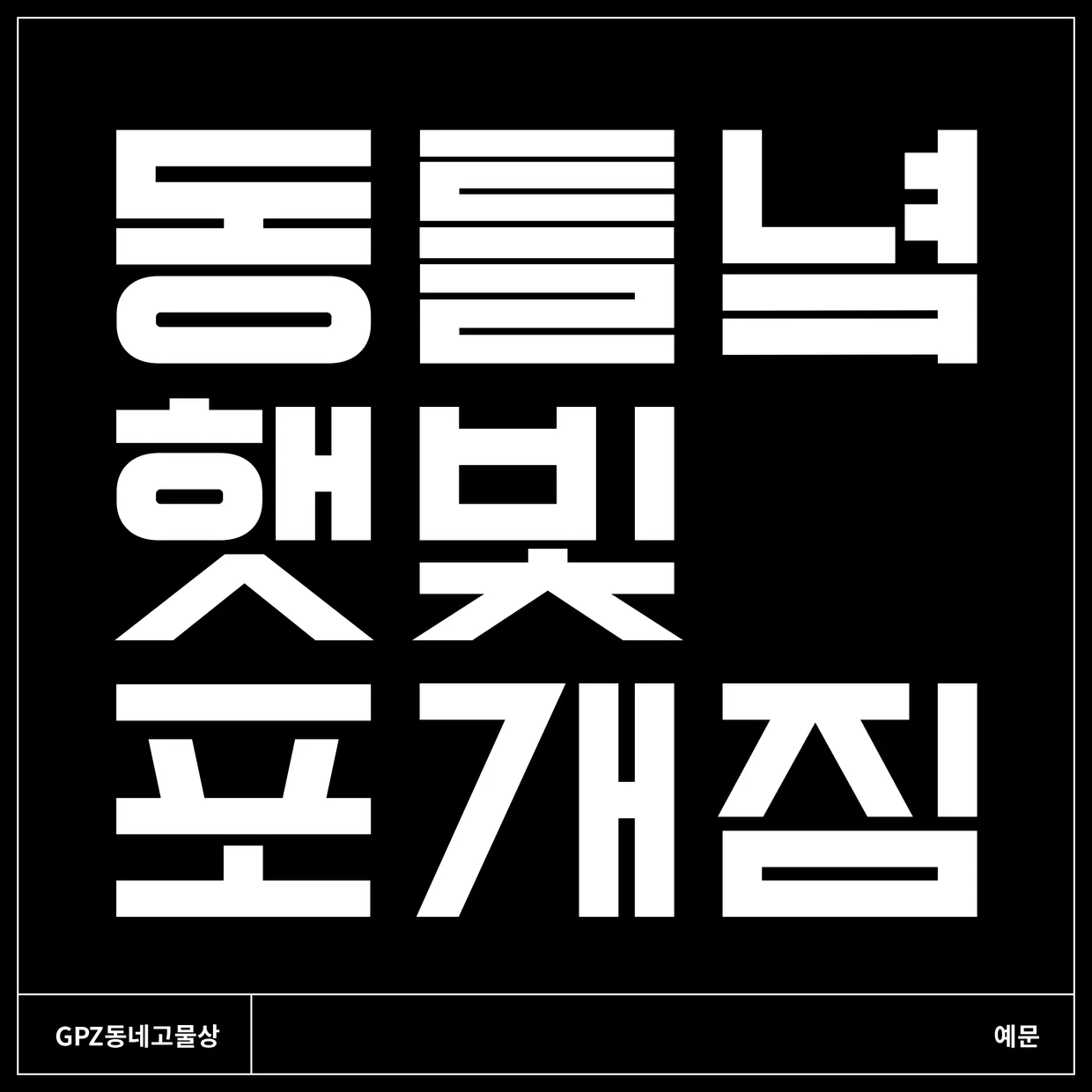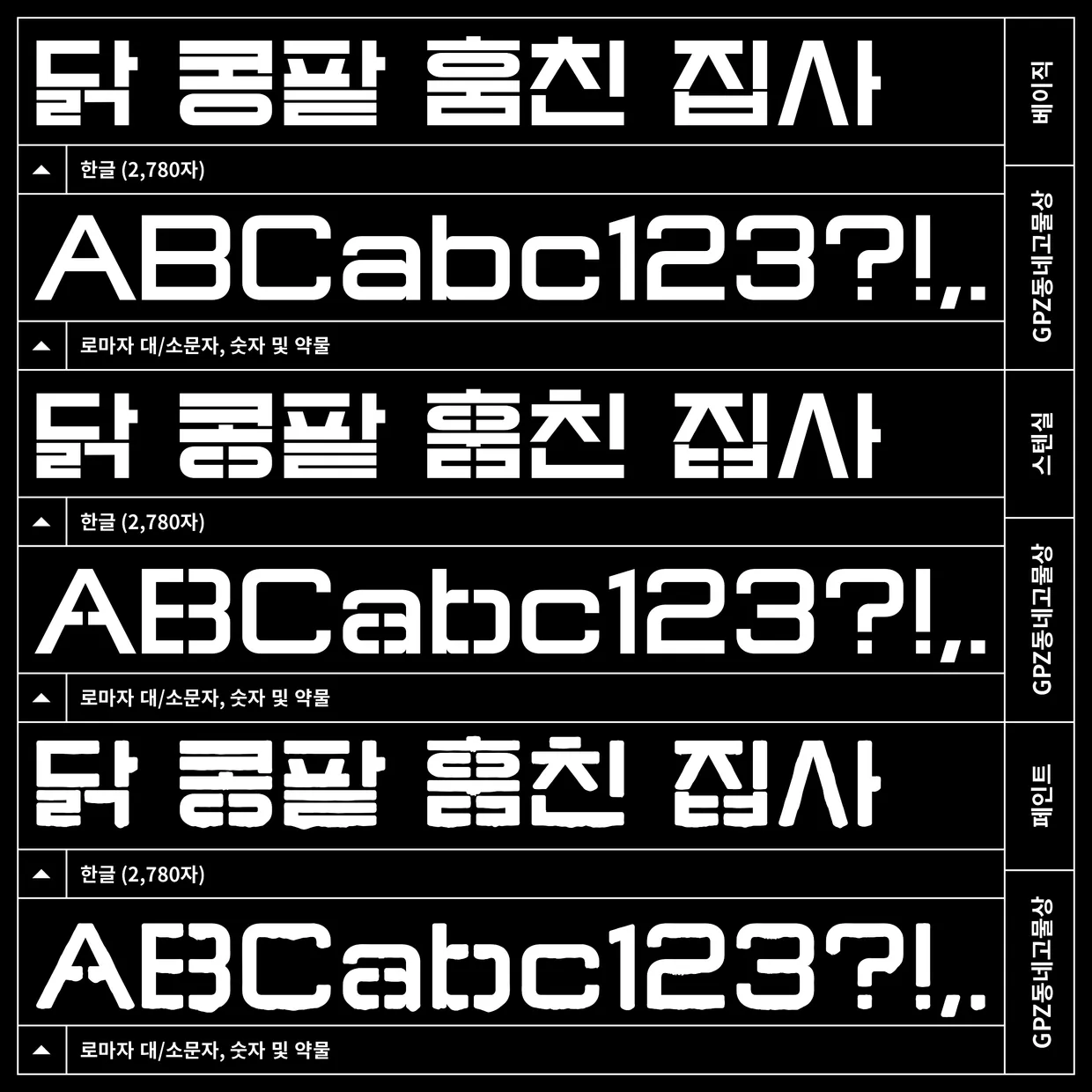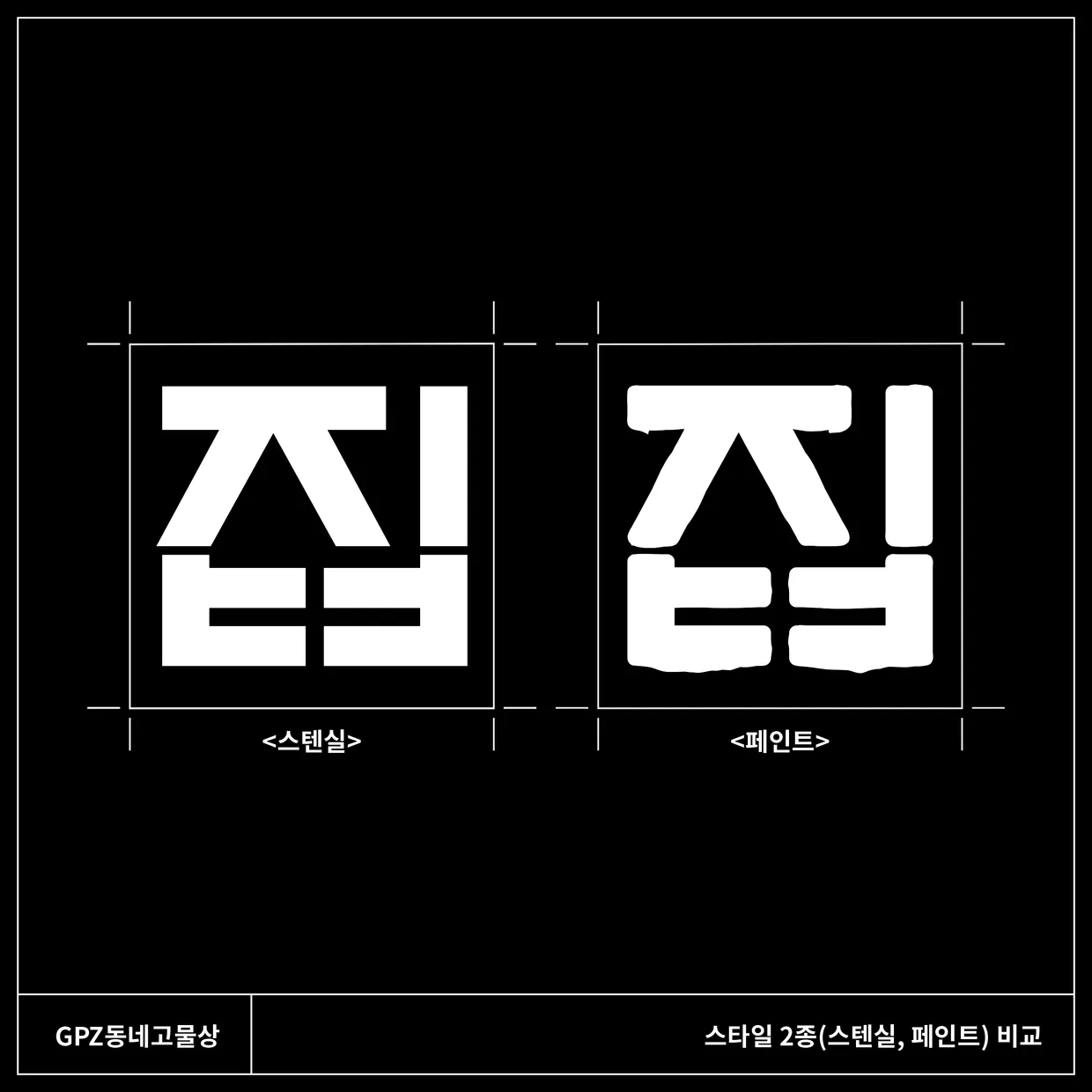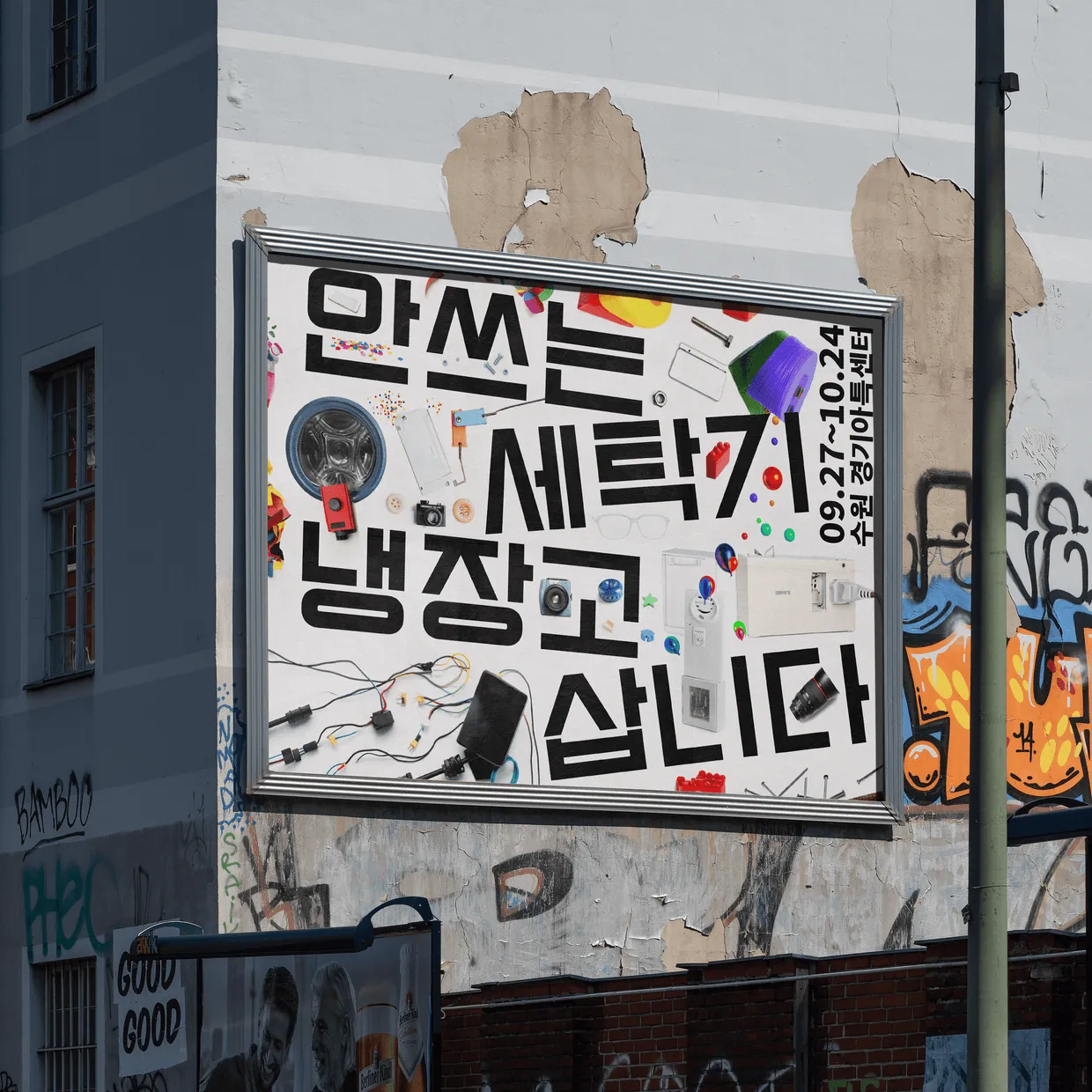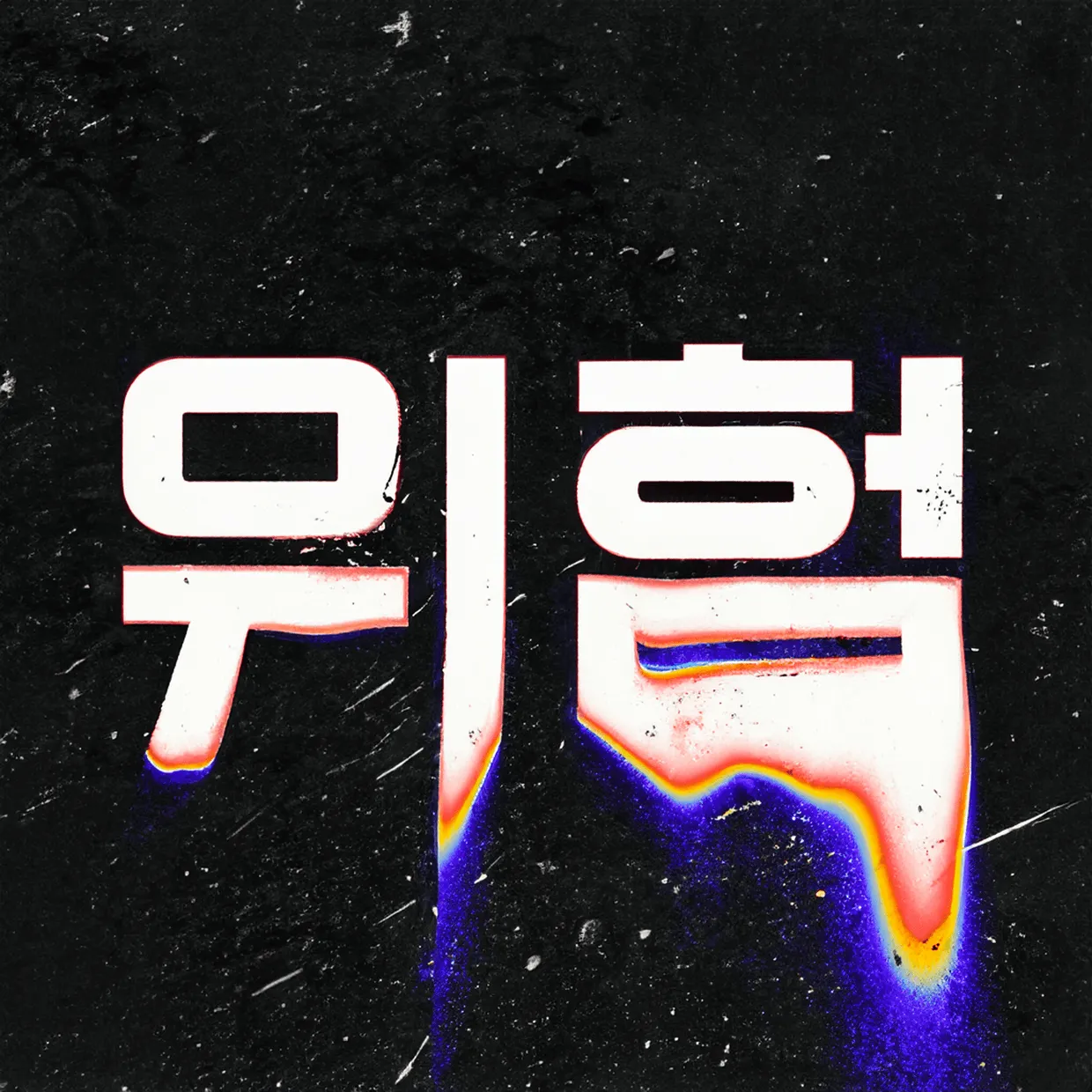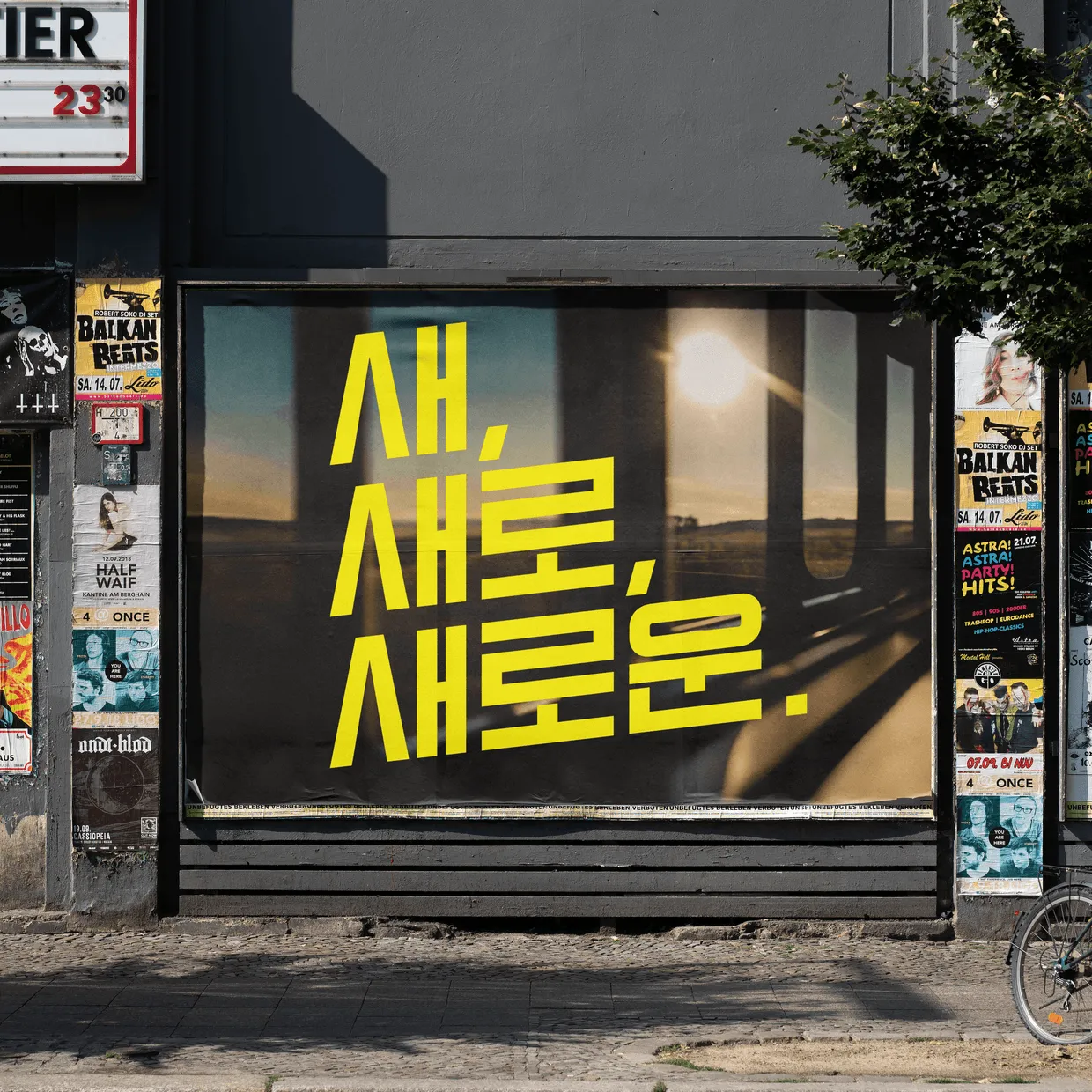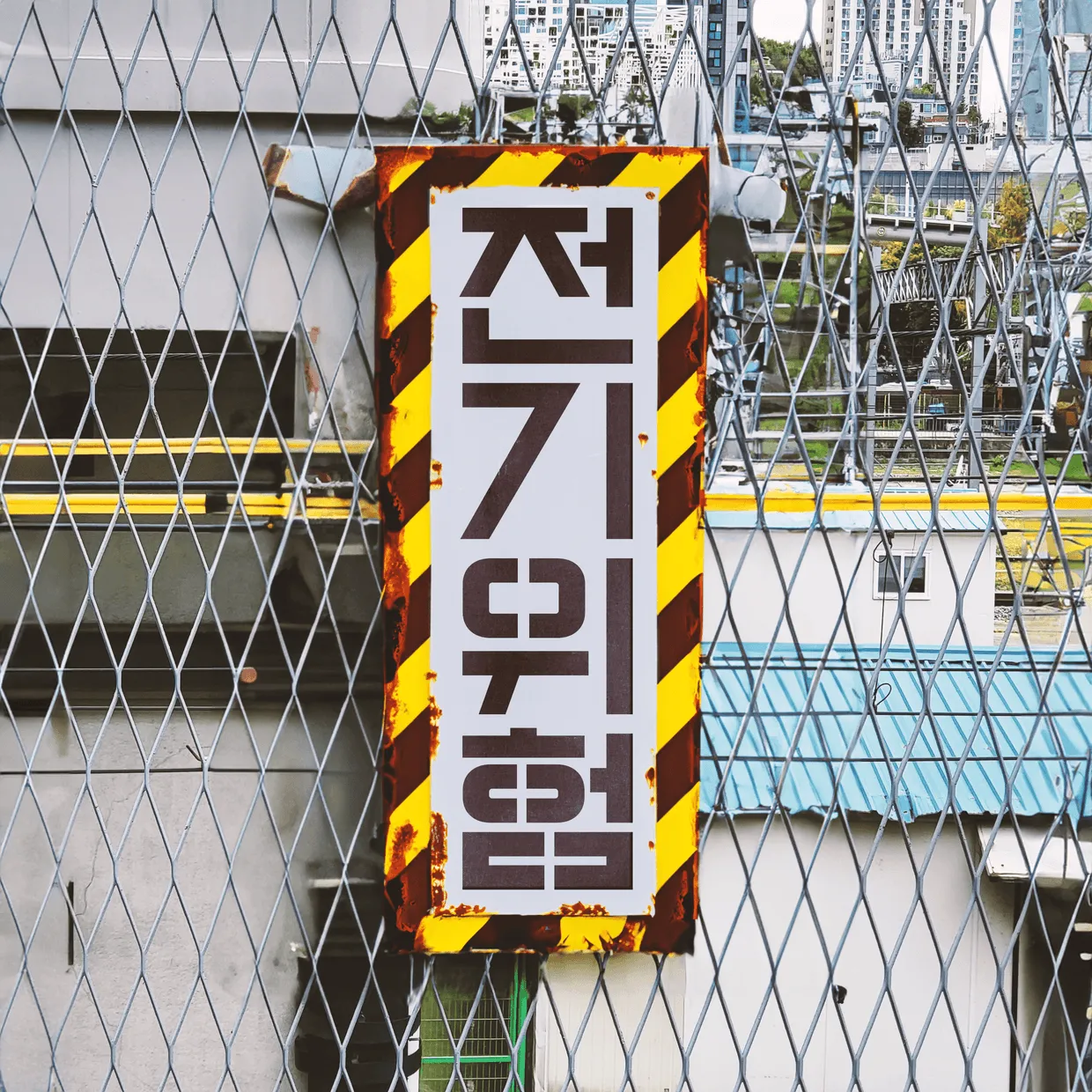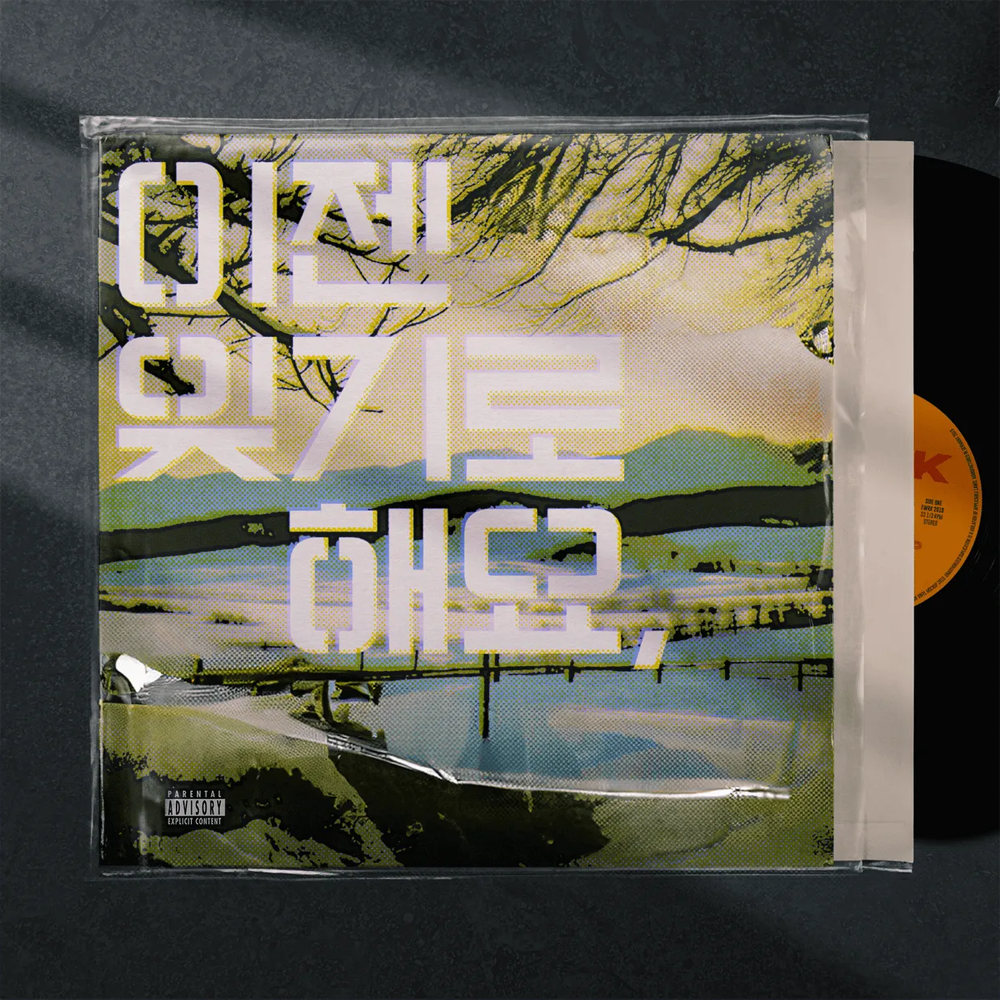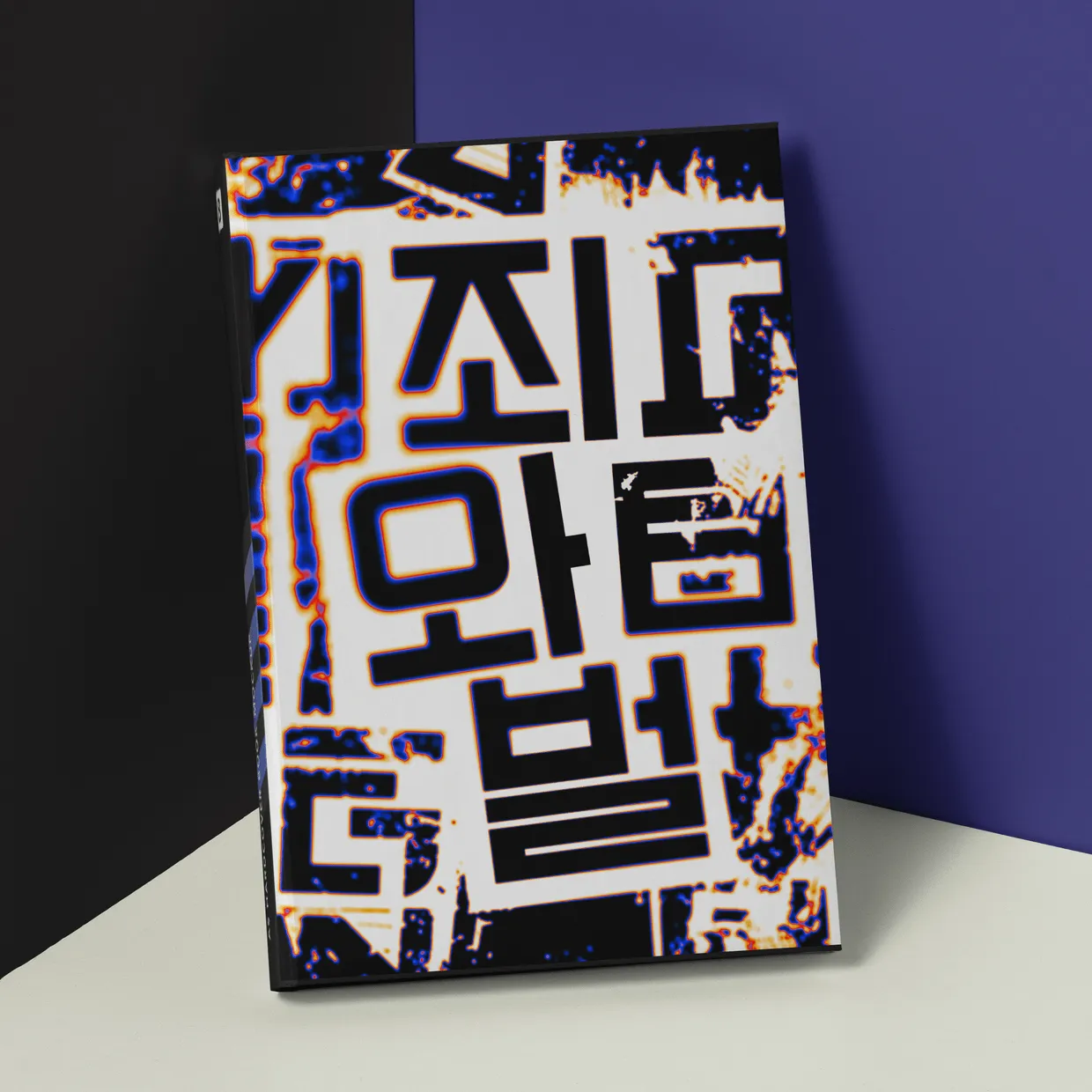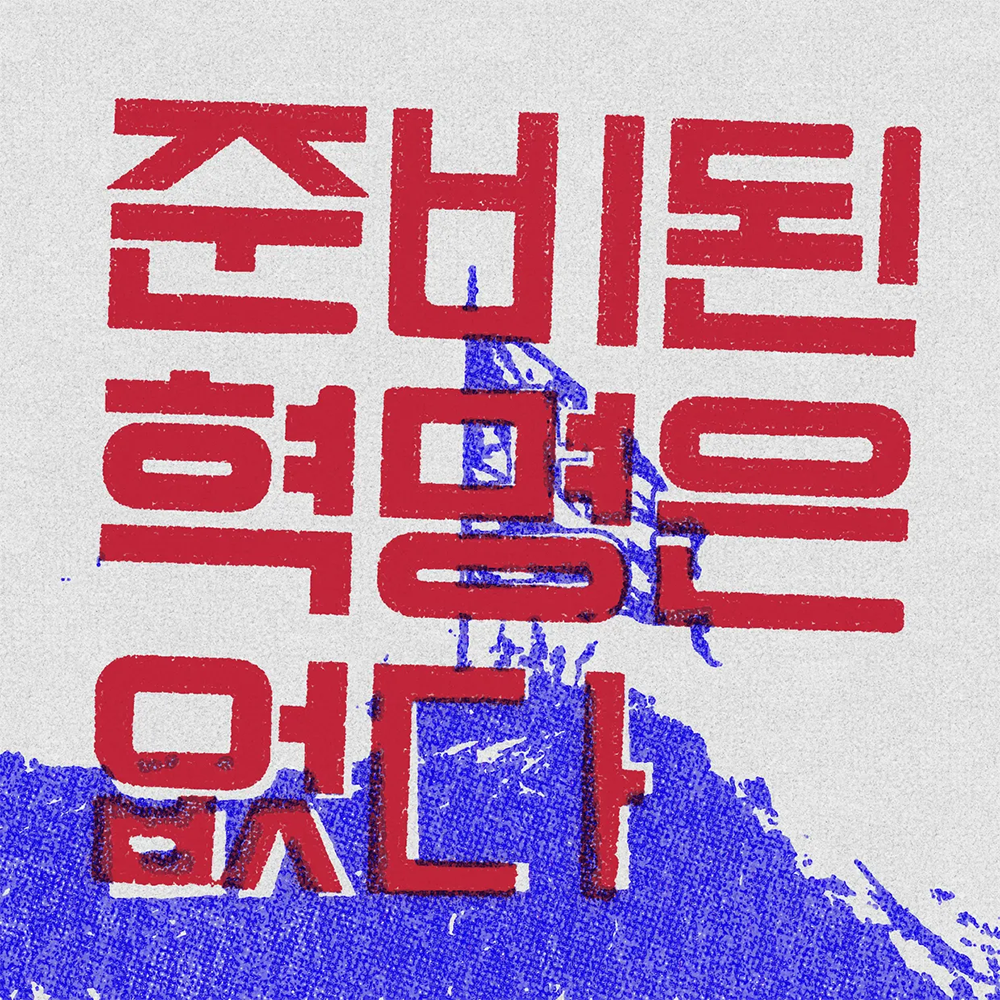
GPZ동네고물상
GPZ 동네고물상의 기본 구조
'GPZ 동네고물상'은 동네에서 흔히 보이던 칠(paint) 글자를 닮은 조합식 서체입니다. 가로로 널찍한 평체의 인상을 보이며, 옛날 판자 속 글씨처럼 주로 수직, 수평으로 획이 만나게 했습니다. 그 이름이 말해주듯 동네 고물상이나 고철상에서 페인트 또는 테이프로 획의 굵기와 그 구조를 곧이 곧대로 드러내는 듯한 모습이 특징입니다.
GPZ 동네고물상의 기본 특징
이때 한글의 모임꼴 구조 상 히읗의 세로줄기나 모음의 가로줄기가 뻗어나가는 경우가 있는대, 이 경우에도 별도로 공간을 보상하지 않고 그대로 두어 투박한 미감을 살렸습니다. 이 때문에 세로로 쓰면 긴 기둥처럼 곧게 세워지는 모습을 보이지만 가로쓰기 할 때에는 다소 공간이 차이 나 보일 수 있습니다.
GPZ 동네고물상의 자음 생김새
'GPZ 동네고물상'은 모임꼴에 따라 차이는 있지만 '상'에서 특히 보이듯 초성 자음이 크게 그려진 서체입니다. 앞서 말한 여러 조형적 요소로 단조롭고 투박하기 때문에 본문보다는 제목에 어울리며, 복고적 인상을 더해야 할 때 또는 주목도 높고 독특한 미감의 글자가 필요할 때 사용하면 좋을 듯 싶습니다.
GPZ 동네고물상의 구성과 스타일
GPZ 동네고물상의 스타일 상세 모습
'GPZ동네고물상'은 한글 2,780자에 로마자 대/소문자를 포함하며 숫자와 약물 및 추가자로 구성됩니다. 스타일에는 기본이 되는 '베이직'과 칠 글자 특유의 이음새를 따라한 '스텐실', 직접 칠한 듯한 '페인트'로 총 3종이 있습니다. '스텐실'과 '페인트'는 얼핏 비슷하지만, 페인트는 직접 칠한 것처럼 물감이 거칠게 흐르는 질감이 그대로 드러나 있는 점이 다릅니다.